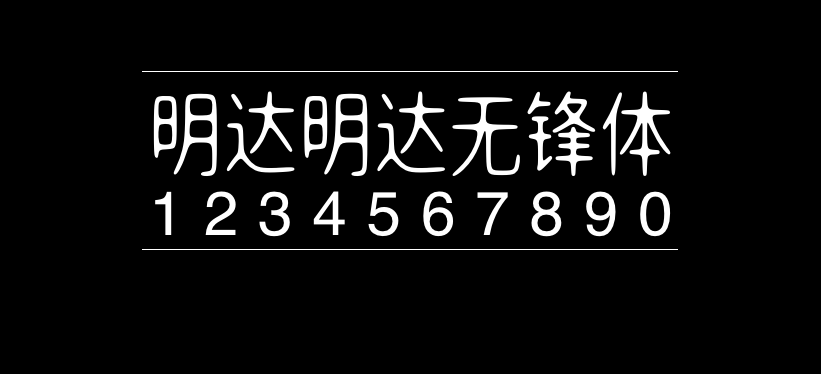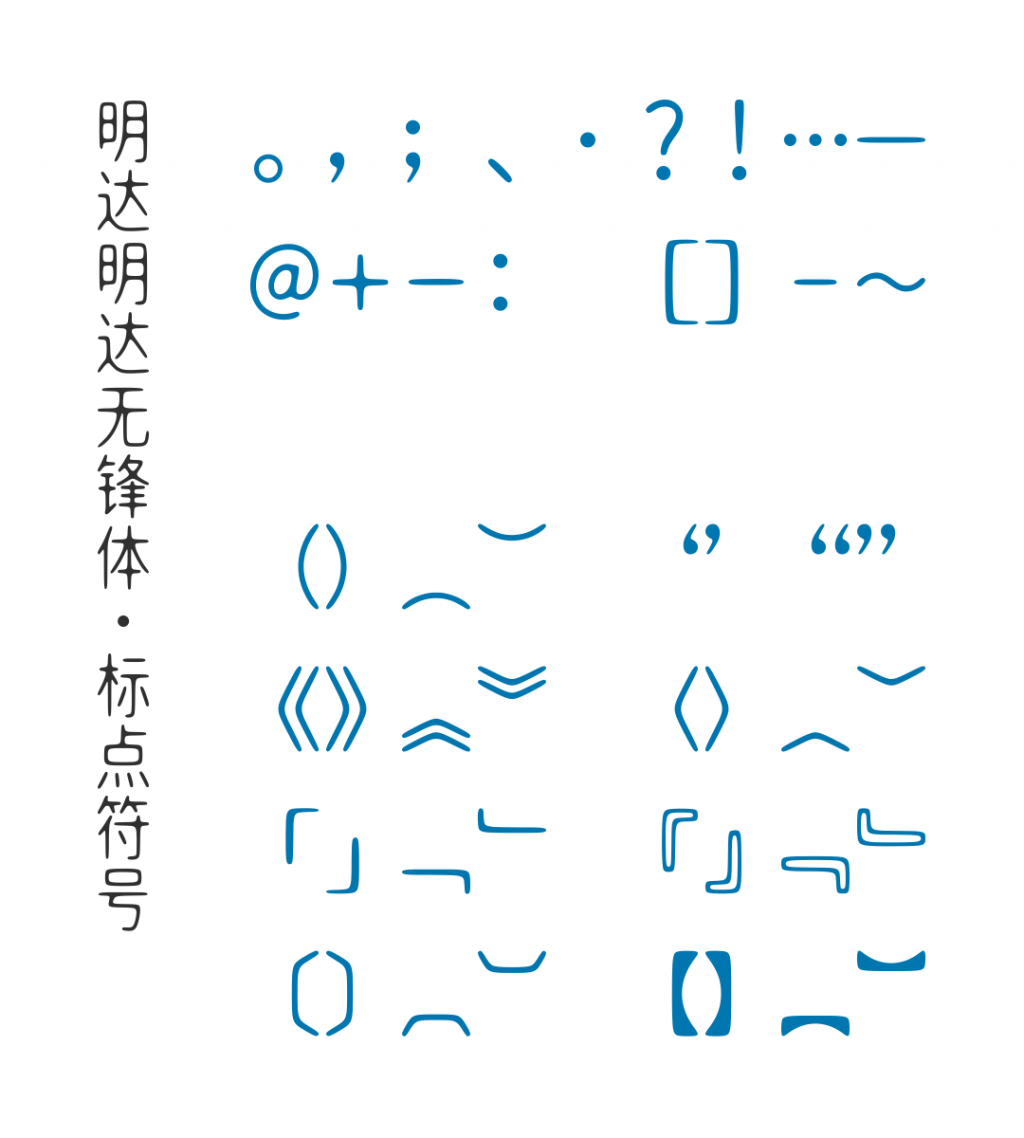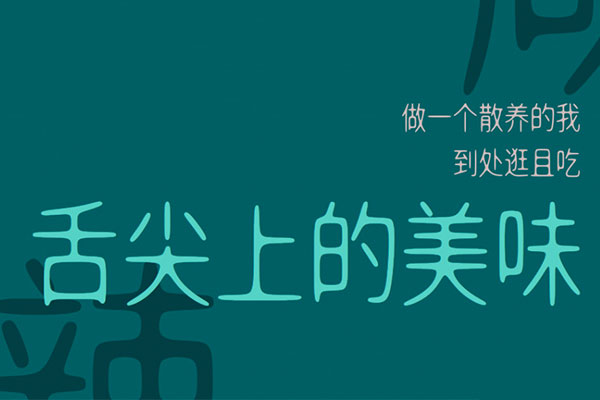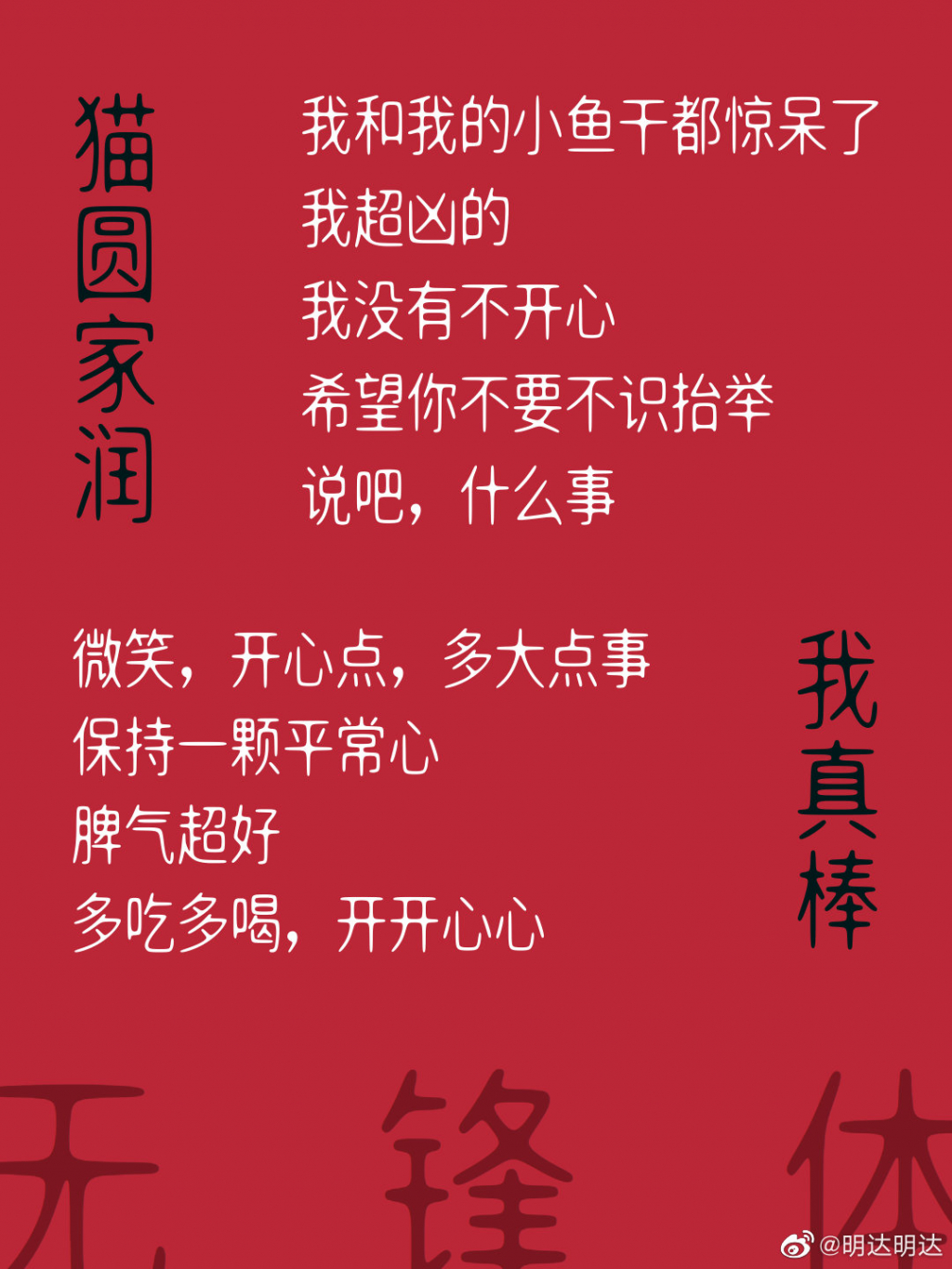
明达明达无锋体
明达明达无锋体是微博网友”明达明达“发布的一款免费商用字体。
明达明达无锋体包含GB2312中的6763个汉字和49个全角中文标点符号。(不含英文、数字)
明达明达无锋体特点:中宫放松,布局舒展,步进等宽;笔划略细,字身稍长,高:宽=5:4。笔划布局上采用中宫放松的黑体布局。在大体布局上参考思源黑体(布局很均匀)和以前宣传画的各种竖型字体,根据具体笔划形态冲突、重心变化、美观平衡做调整。似水的凝聚形成“墨的无锋”,浑圆无折角,无笔锋,故名“无锋体”。